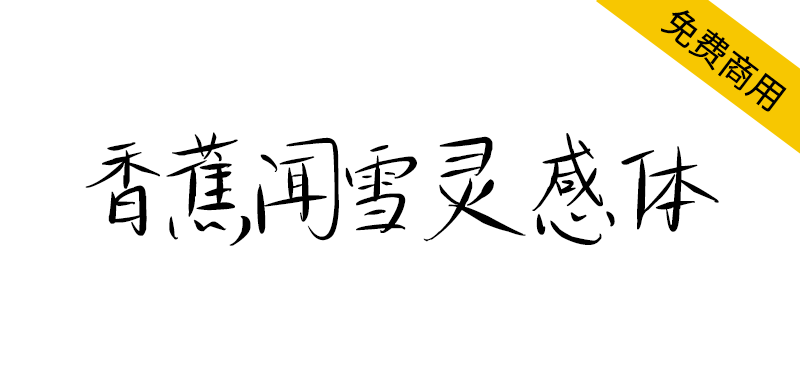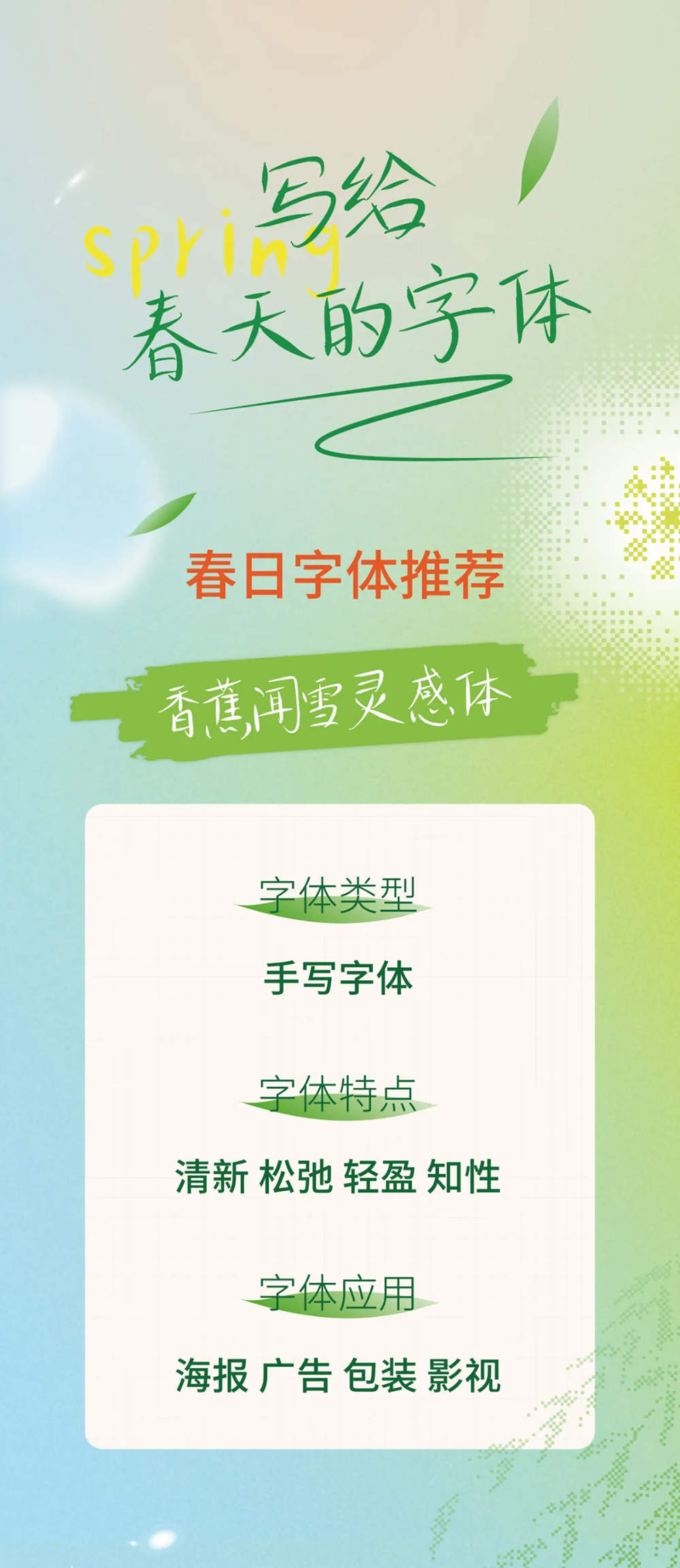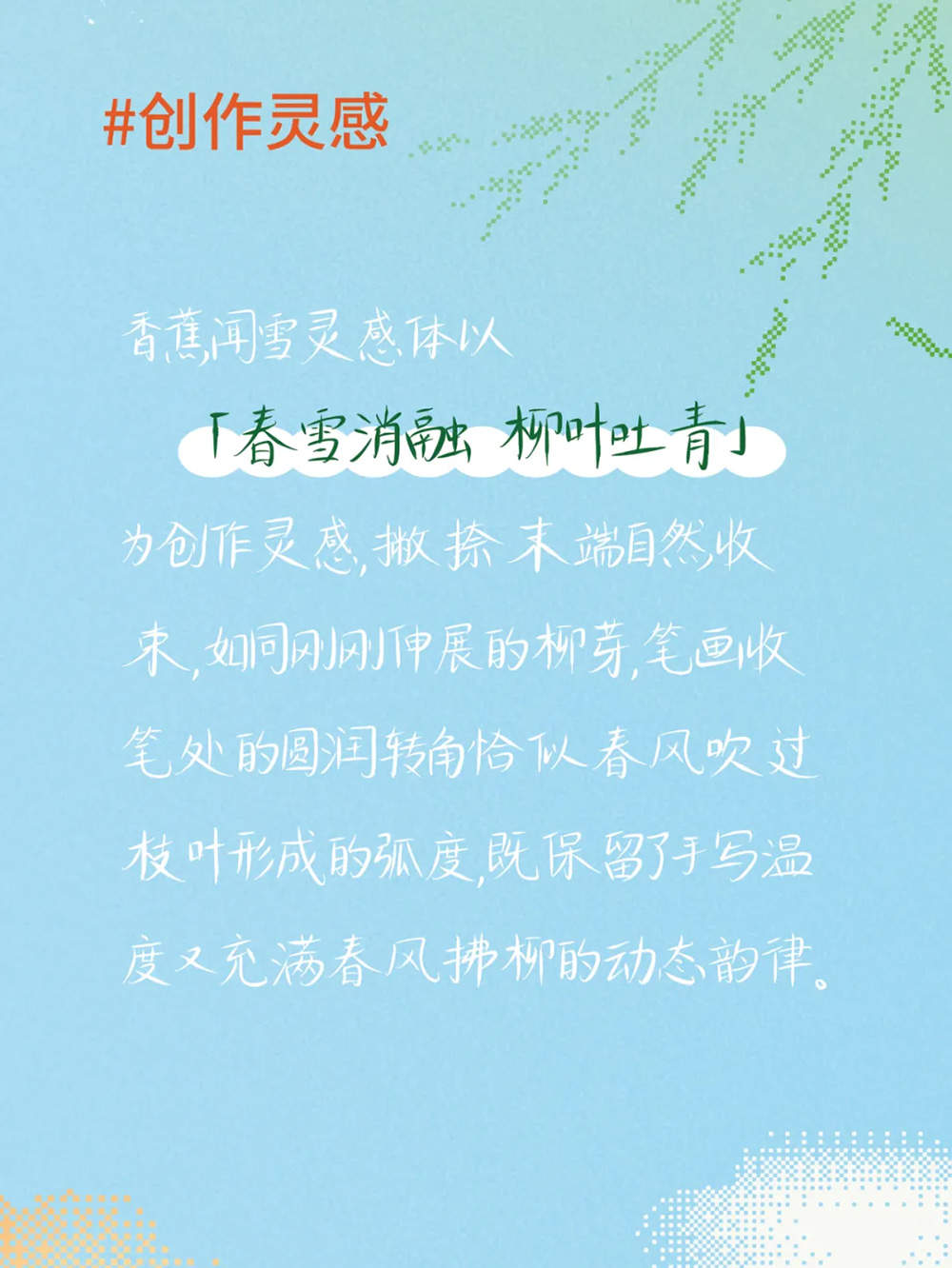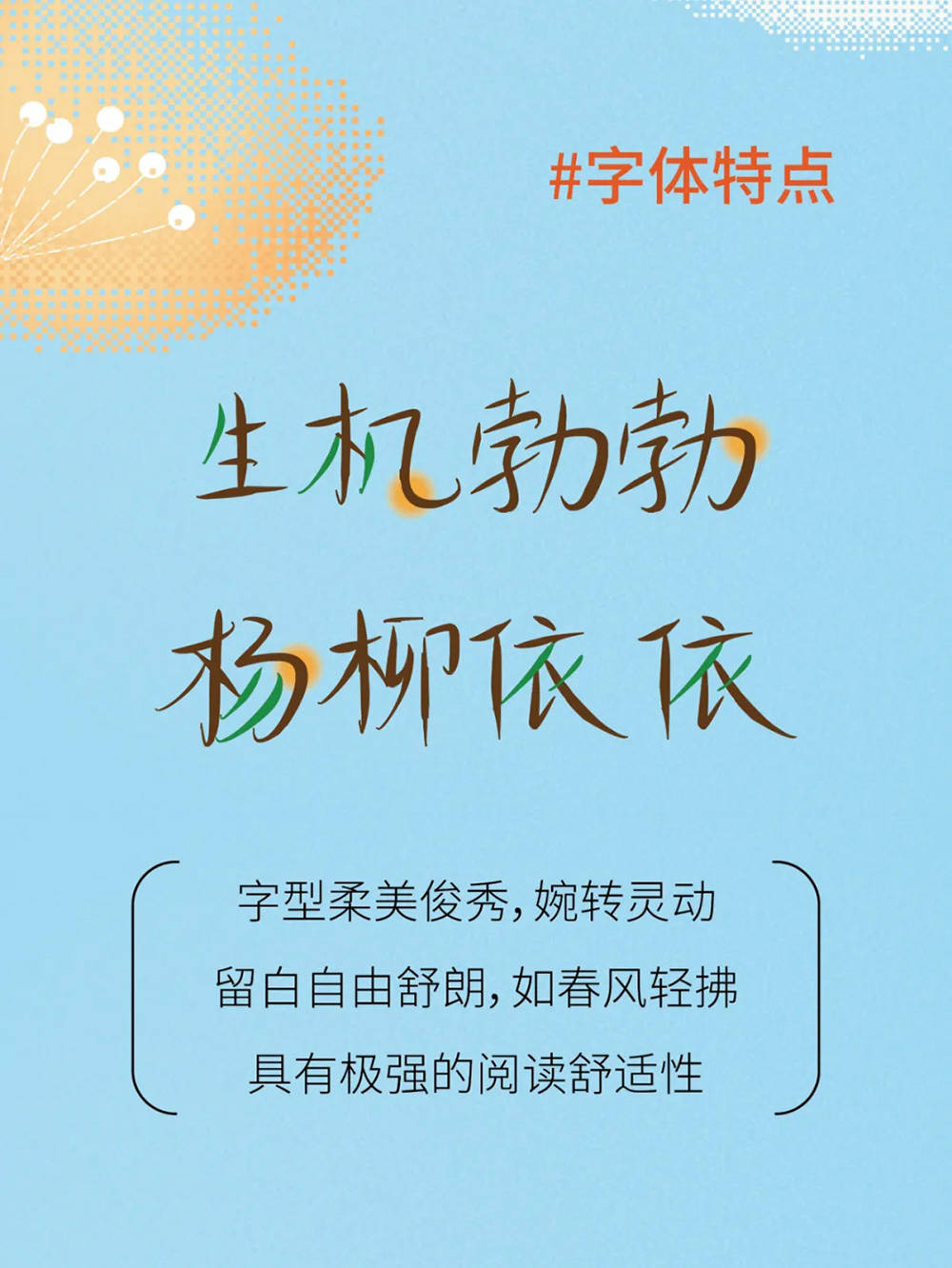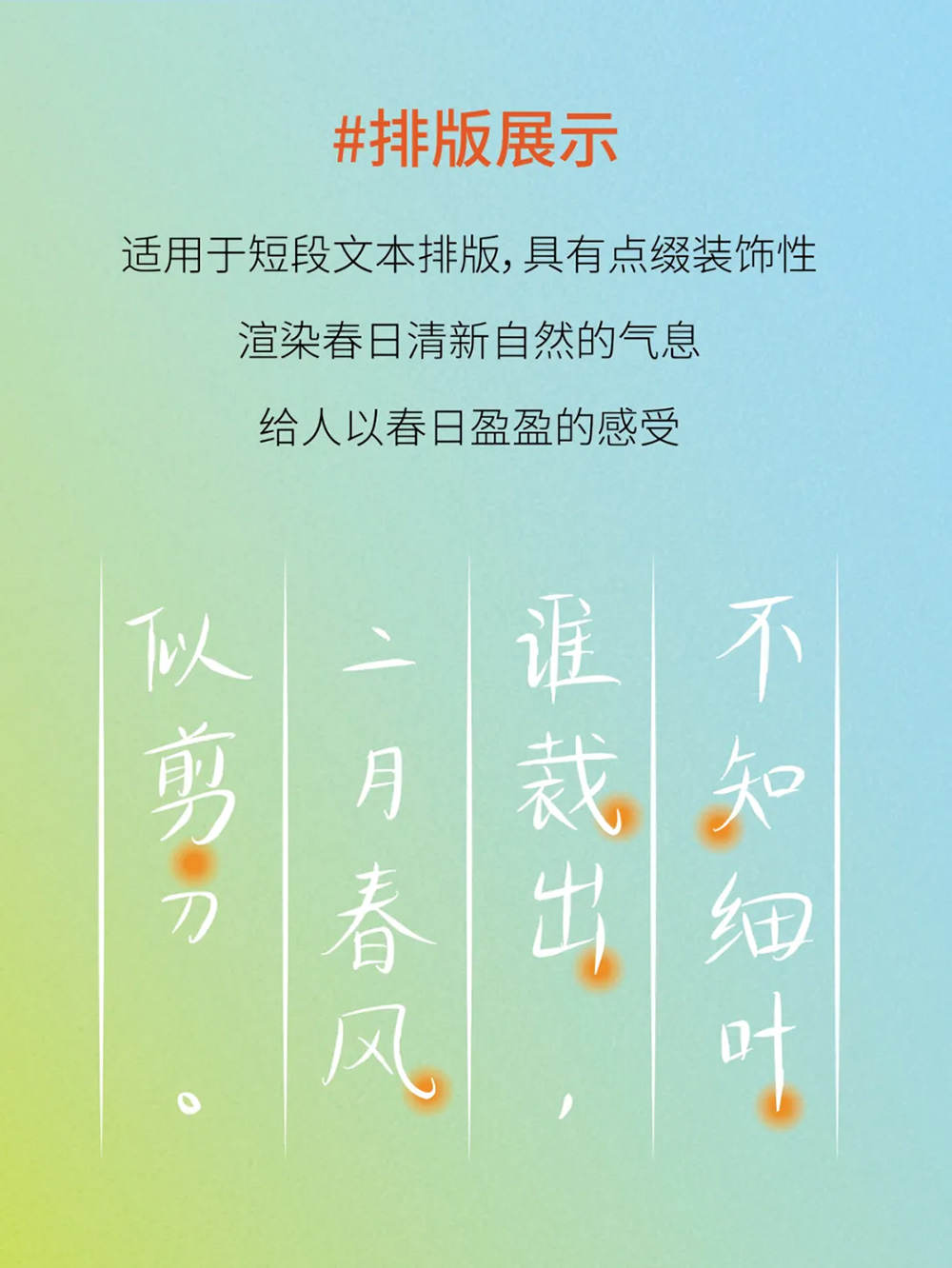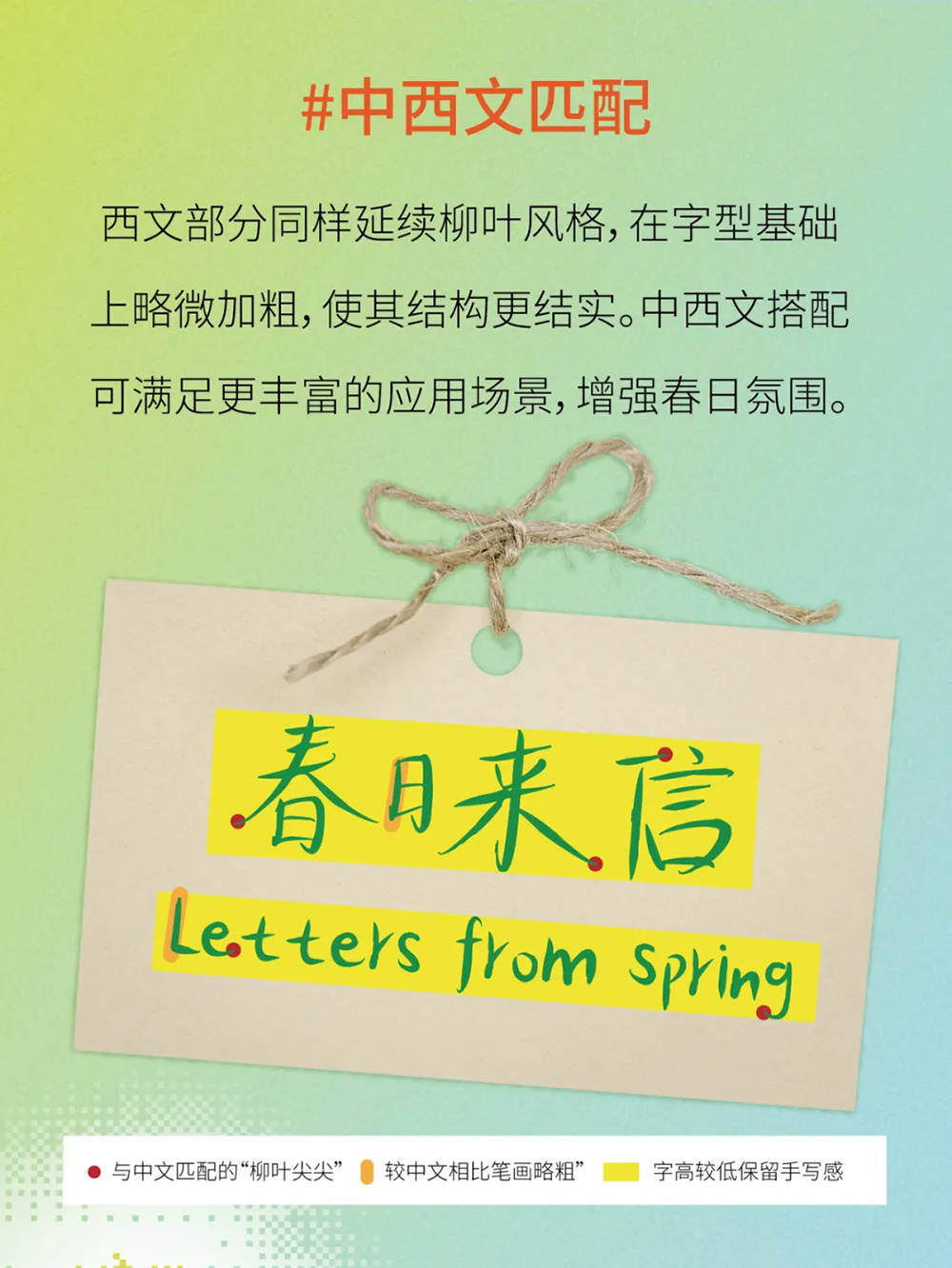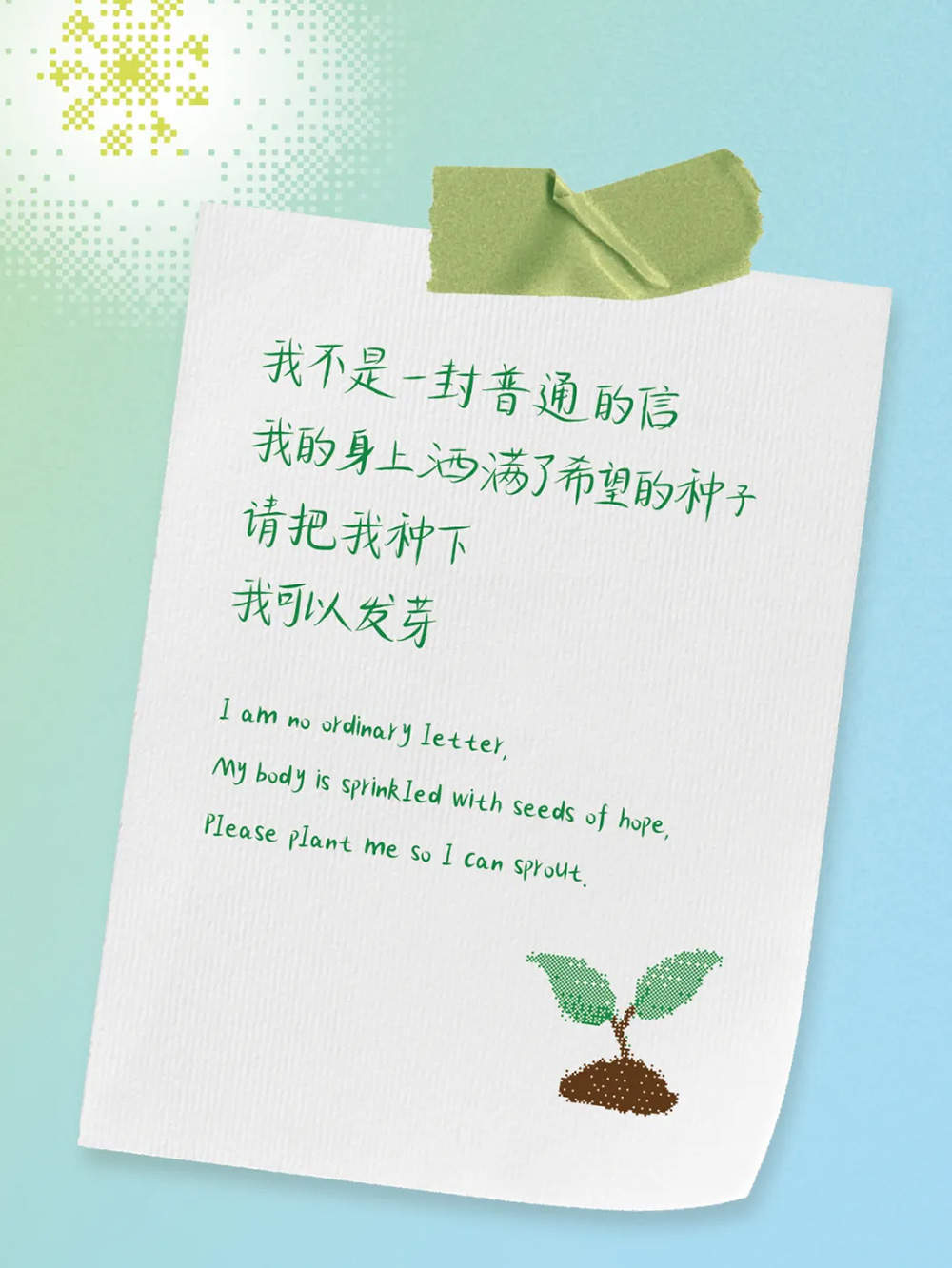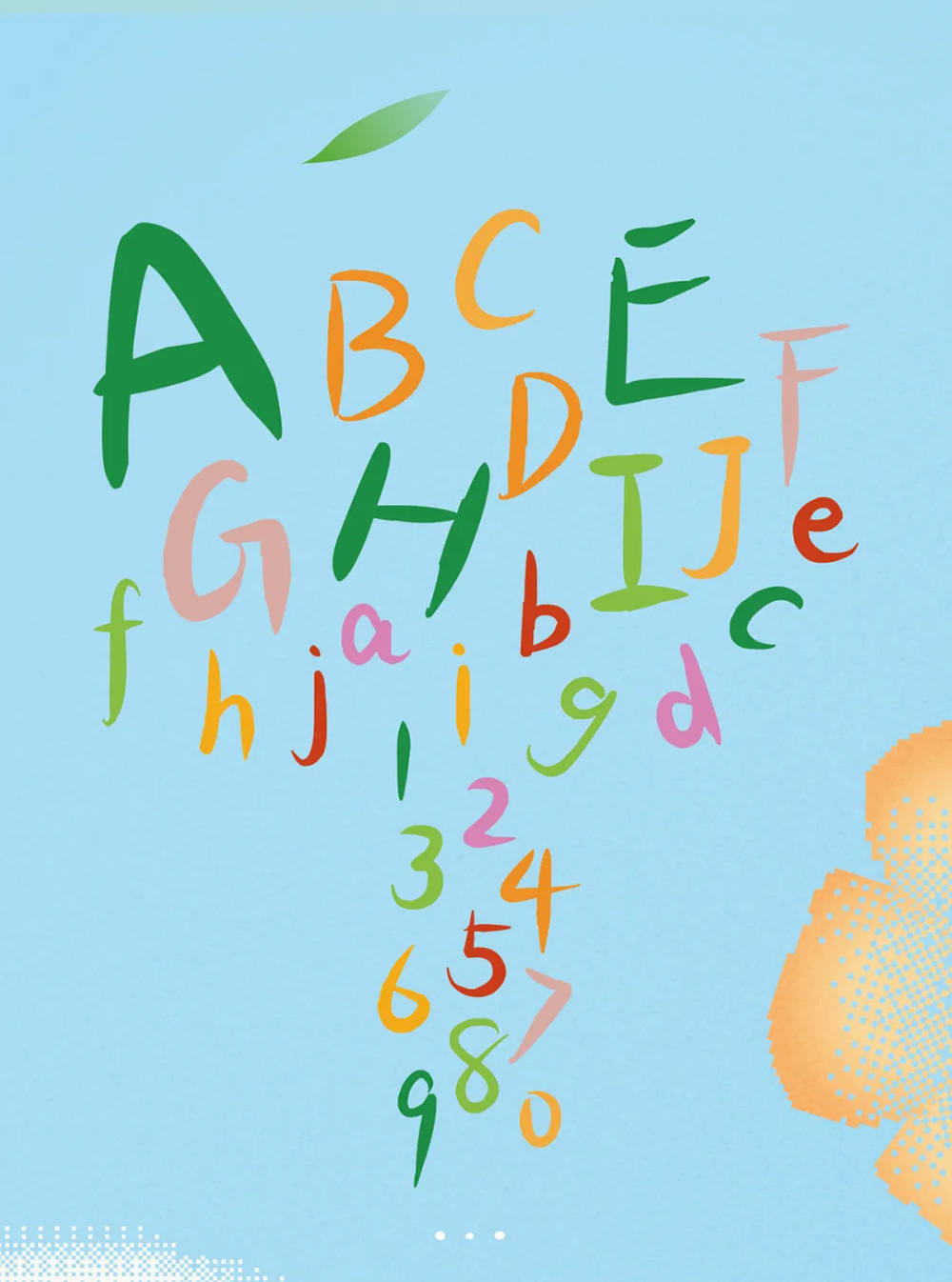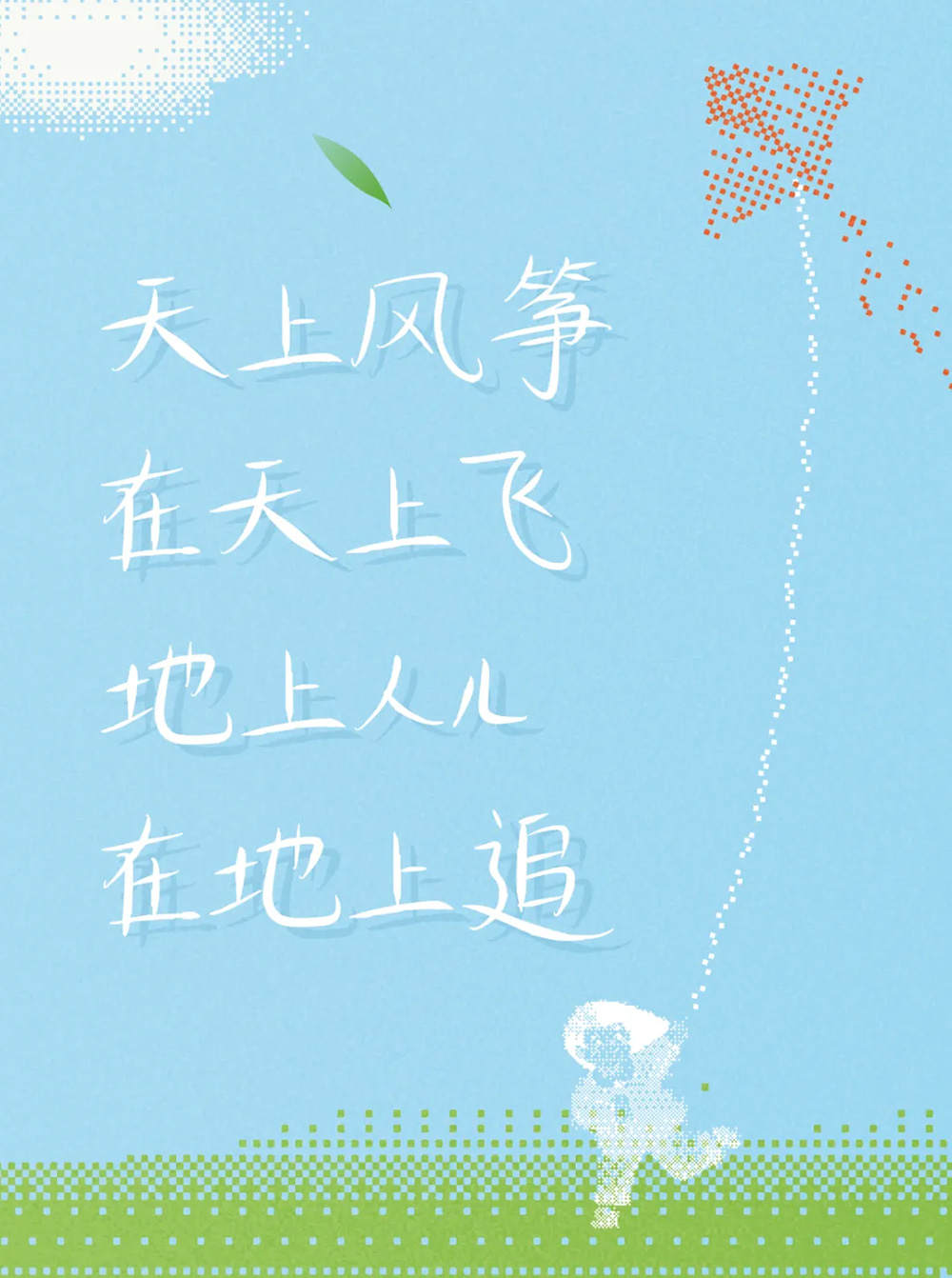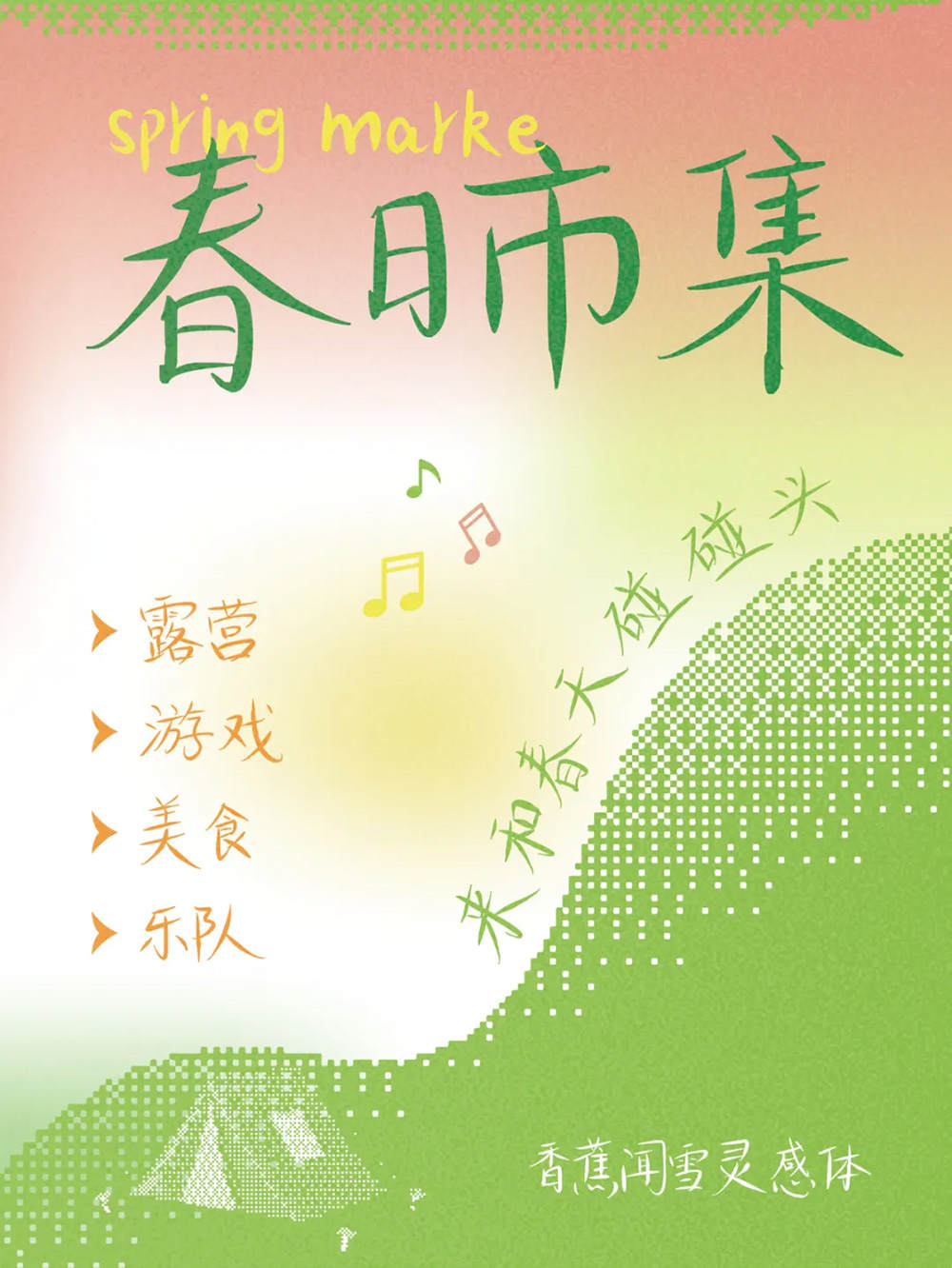
【香蕉闻雪灵感体】字形俊秀、婉转灵动,透出知性之气
你见过为“冬日初雪”而生的字体吗?香蕉闻雪灵感体,字如其名,笔画婉转灵动,柔美中带着知性气质,仿佛雪花落在纸上的瞬间被凝固成字。6864个汉字,支持商用,免费可下载,适合设计、自媒体、电商等各类场景。它不只是字体,更是一种情绪的表达。你想用它写下怎样的故事?
【香蕉闻雪灵感体】字形俊秀、婉转灵动,透出知性之气
香蕉闻雪灵感体,字形俊秀、婉转灵动,透出知性之气。笔画柔美俊秀、刚柔并济,自然洒脱中透露出对冬日第一场雪的期望。本字体为简体字库,采用OpenType格式,基于中华人民共和国GB2312-80字符集标准,另按需添加101个汉字。共收容字数6864汉字,常用符号100个,共计字符6964个。
【香蕉闻雪灵感体】字形俊秀、婉转灵动,透出知性之气